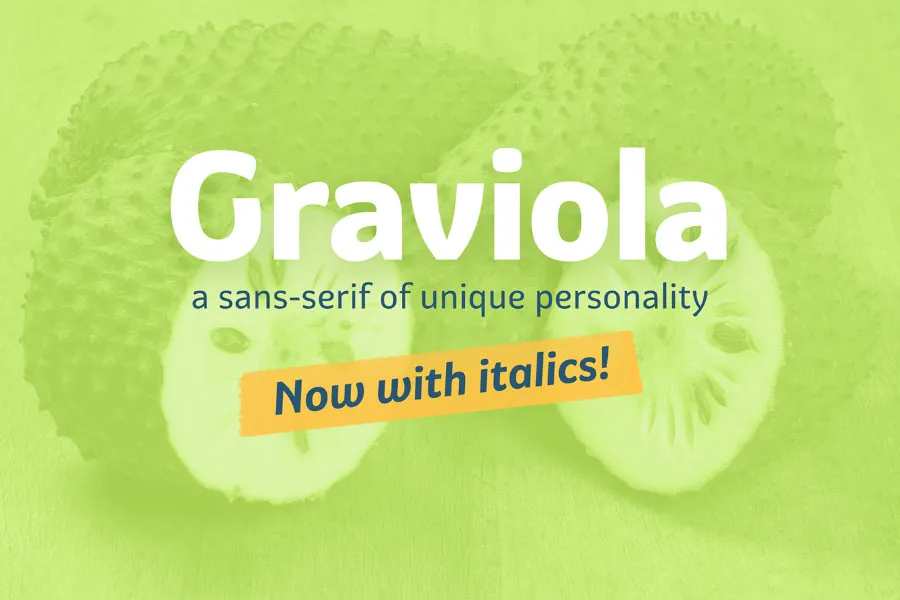
Graviola é uma família de fontes sans-serif que oferece uma sensação de conforto e amabilidade, graças às terminações semi-arredondadas. Esta fonte vem em 16 pesos diferentes, desde ligeiro até grosso, todos acompanhados por suas versões itálicas. A familia completa oferece um vasto conjunto de caracteres que vai do texto principal ao uso no design gráfico e publicitário. Para aqueles que procuram uma fonte para uso em grandes tamanhos e para destaque, o Graviola apresenta resultados impressionantes. Seus pesos mais extremos não apenas dão uma sensação de peso e profundidade, mas também oferecem um visual belamente detalhado, com mais de 530 caracteres em cada face. O design elegante do Graviola inclui suporte a mais de 90 idiomas, fazendo deste fonte uma escolha versátil para qualquer projeto internacional. Ideal tanto para textos legíveis quanto para criações visuais impactantes, esta família de fontes foi criada pensando em designers que buscam uma combinação atraente e eficaz de beleza visual e facilidade de uso.